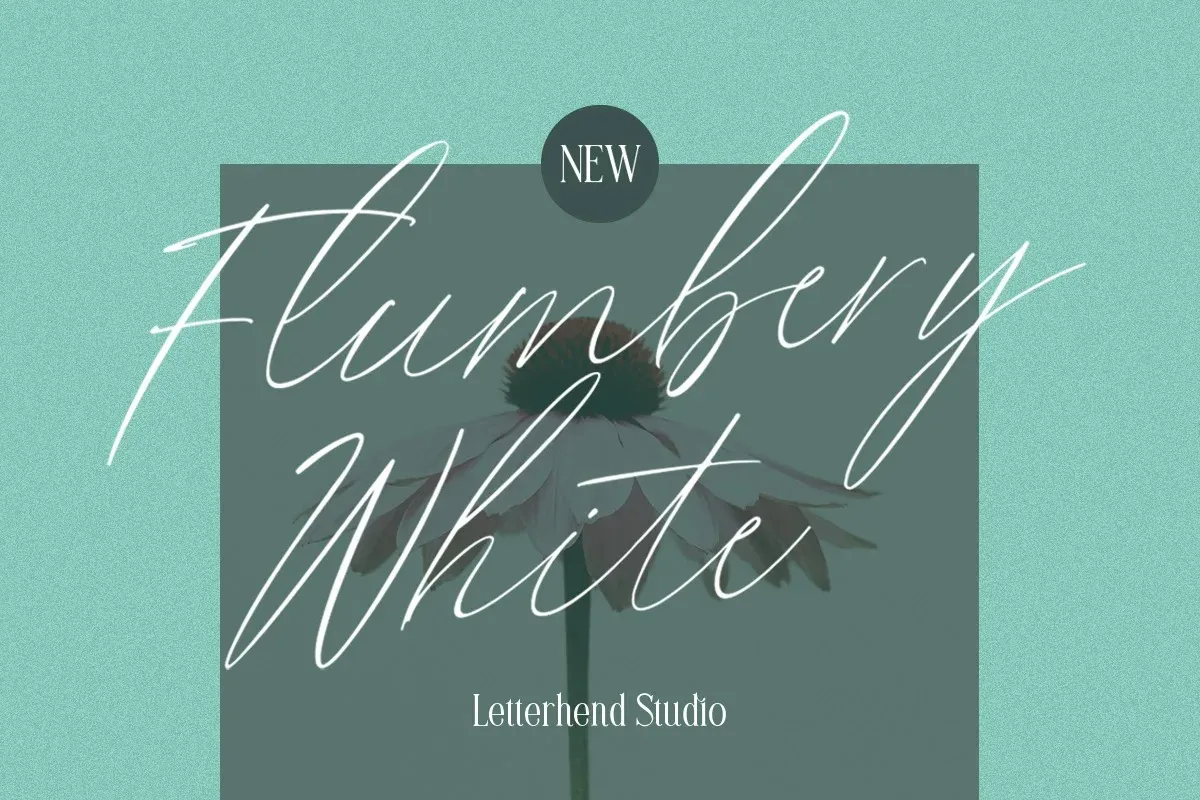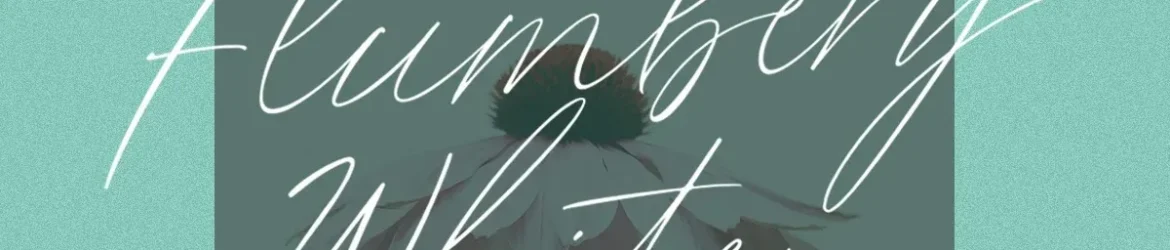
A fonte Flumbery White é uma elegante tipografia script criada pelo designer Letterhend Studio. Ideal para aplicar desde a criação de marcas até headlines em diversos contextos, esta fonte tem um amplo espectro de uso que vai muito além do logotipo. Conhecida por sua versatilidade e facilidade de leitura, Flumbery White é especialmente adequada para formatos formais como convites, etiquetas, marcas, revistas, livros, cartões de cumprimentos ou cartas de noiva, embalagens, moda e maquiagem, estaçãoamento e até mesmo anúncios. Com seu ar maciço e fluido, Flumbery White é uma ótima escolha para quem busca um toque sofisticado em qualquer projeto gráfico formal. E a sua facilidade de uso torna-a perfeita para designers que procuram criatividade com conforto no design digital.